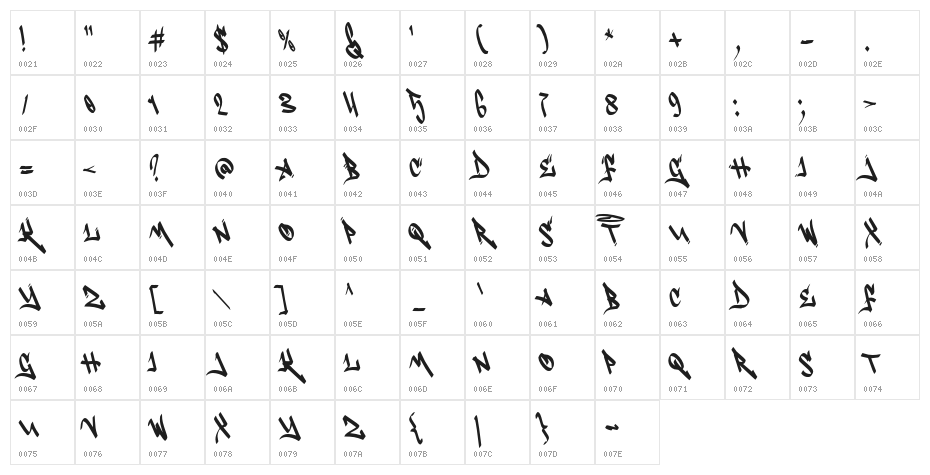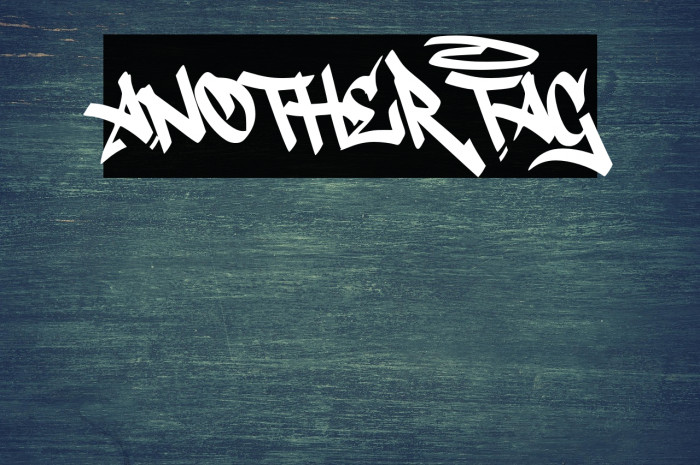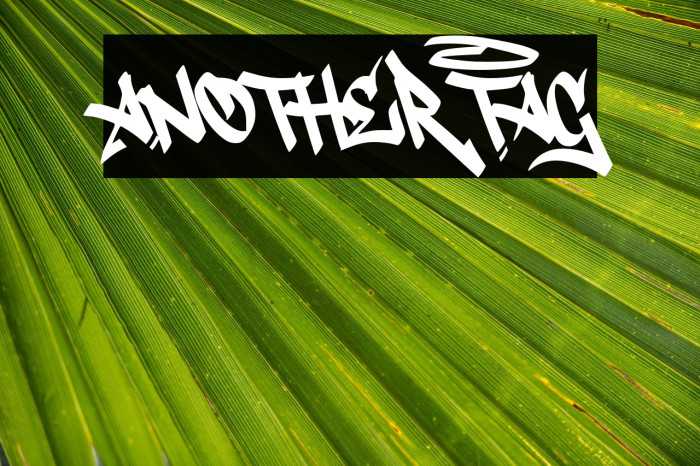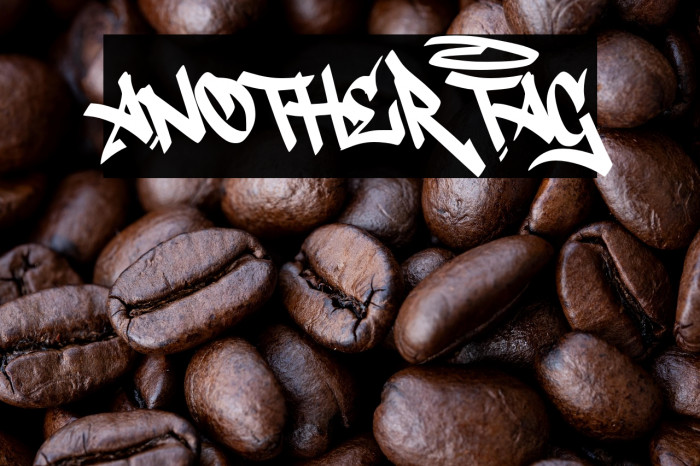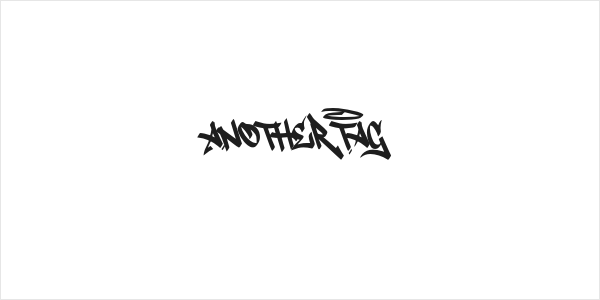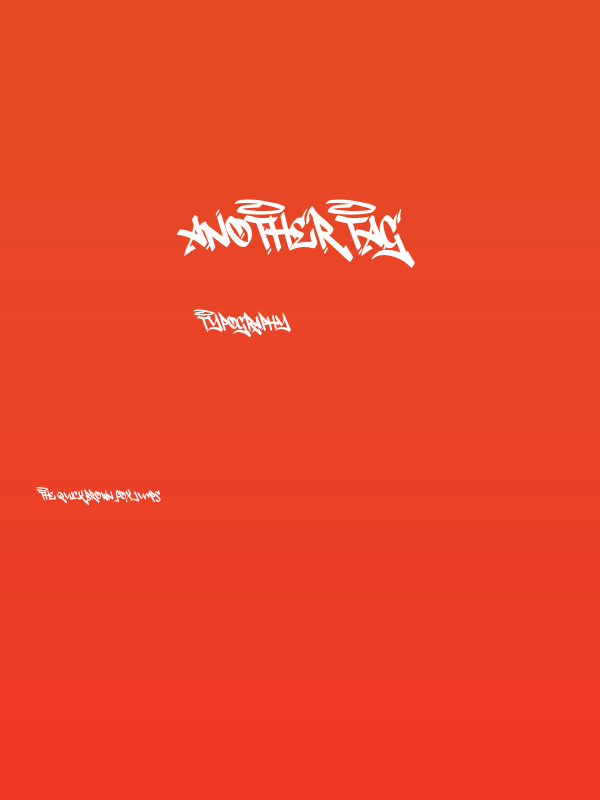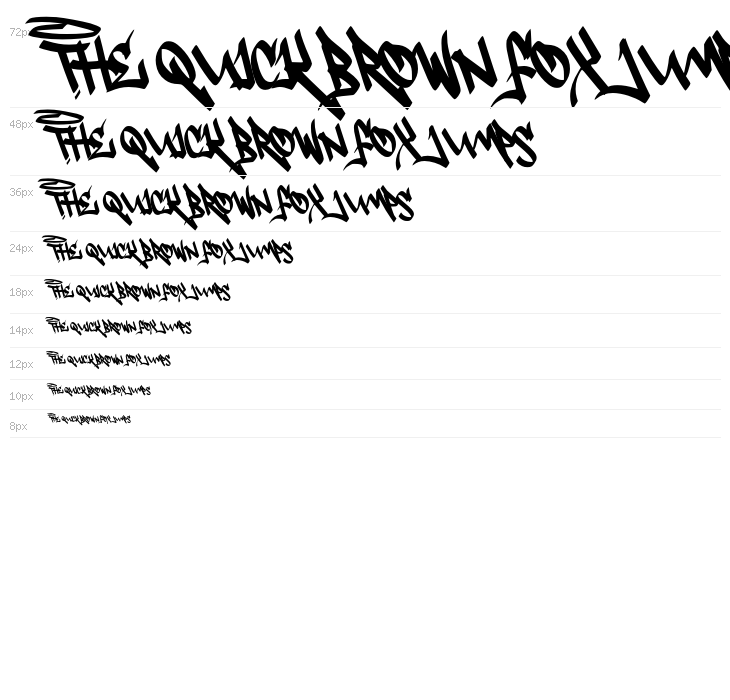
Another Tag Font
✎ Graffiti
| 整体风格 | Urban, Graffiti, Energetic |
| 使用场景 | Logos, Posters, Album Covers |
| 推荐项目 | Perfect for street art-inspired designs, urban-themed posters, music album covers, and edgy branding projects. |